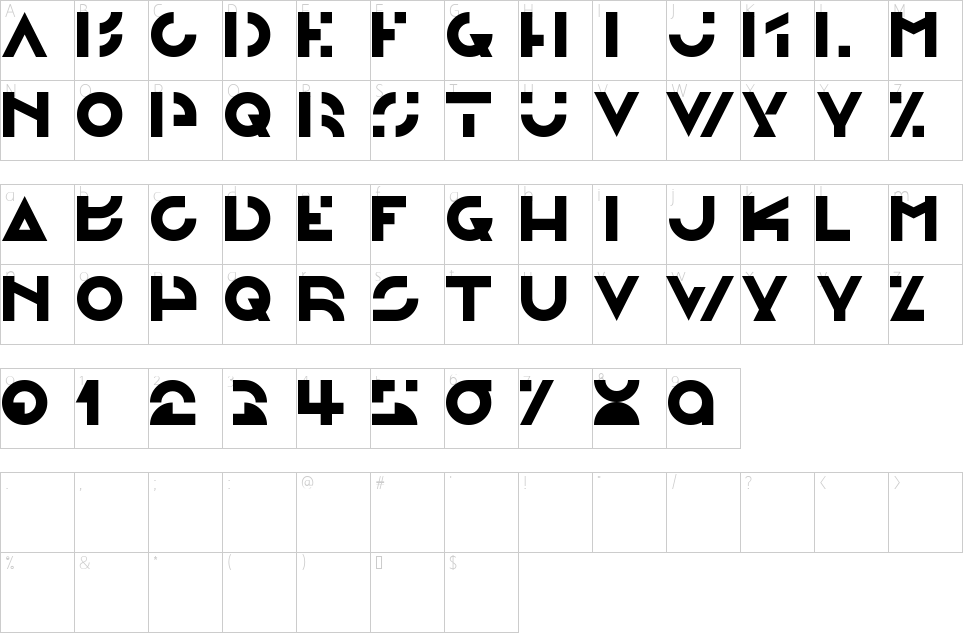
Morgante Font | 1001 Free Fonts – Fonte Grátis
A fonte Morgante é uma opção perfeita para quem procura um estilo natural e envolvente. Esta fonte foi projetada pelo Out Of Step Font Company e já foi baixada mais de 3.953 vezes. Com um design cuidadosamente elaborado, Morgante oferece uma paleta de características que vão bem tanto para escrita formal quanto para fontes em tempo real, tornando-a uma excelente escolha para designers de sites, desenvolvedores de software e designers gráficos. Com sua versão gratuita, é fácil incorporar a beleza e a sofisticação de Morgante em seus projetos digitais. Sem dúvida, ela é uma opção ideal para quem busca uma fonte livre de qualidade, sem compromissos.